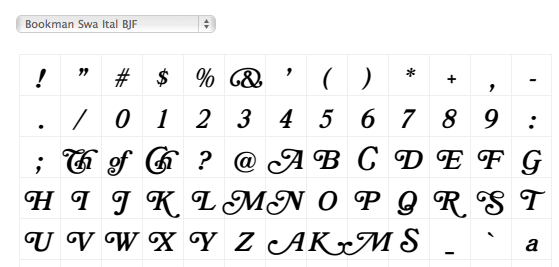
sieht verdammt wie eine bookman mit swashes aus; aber welche genau?
... the first version of Bookman that's faithful to the original, packing in all of the swash variants and alternates for each weight.